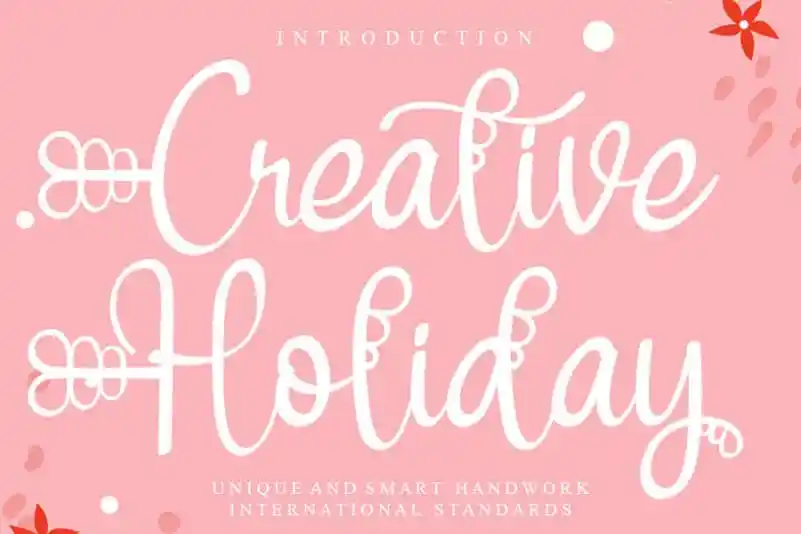
Creative Holiday Script Font
Sinta-se à vontade para adicionar esta fonte ‘Creative Holiday Script Font’ a seu design, seja ele para cartões de aniversário criativos ou e-mails personalizados cheios de vida. Ela é perfeita para criar mensagens únicas que chamam atenção dos olhos e envolvem quem lê com o amor pelo detalhe único e especial que apenas Creative Letter pode oferecer. Criado por Designer: creativeletter, esta fonte Script destaca-se por suas letras suaves e fluidas, proporcionando um toque de alegria e personalização à sua criação. Seja para nomear seus produtos de uma maneira que destaque o seu diferencial ou imprimir mensagens surpreendentes em cartões de aniversário, esta fonte é certamente um item indispensável no seu arsenal gráfico. Combinada com a expertise dos designers da Creative Letter, ela oferece experiências excepcionais e personalizadas para qualquer projeto que você esteja criando.